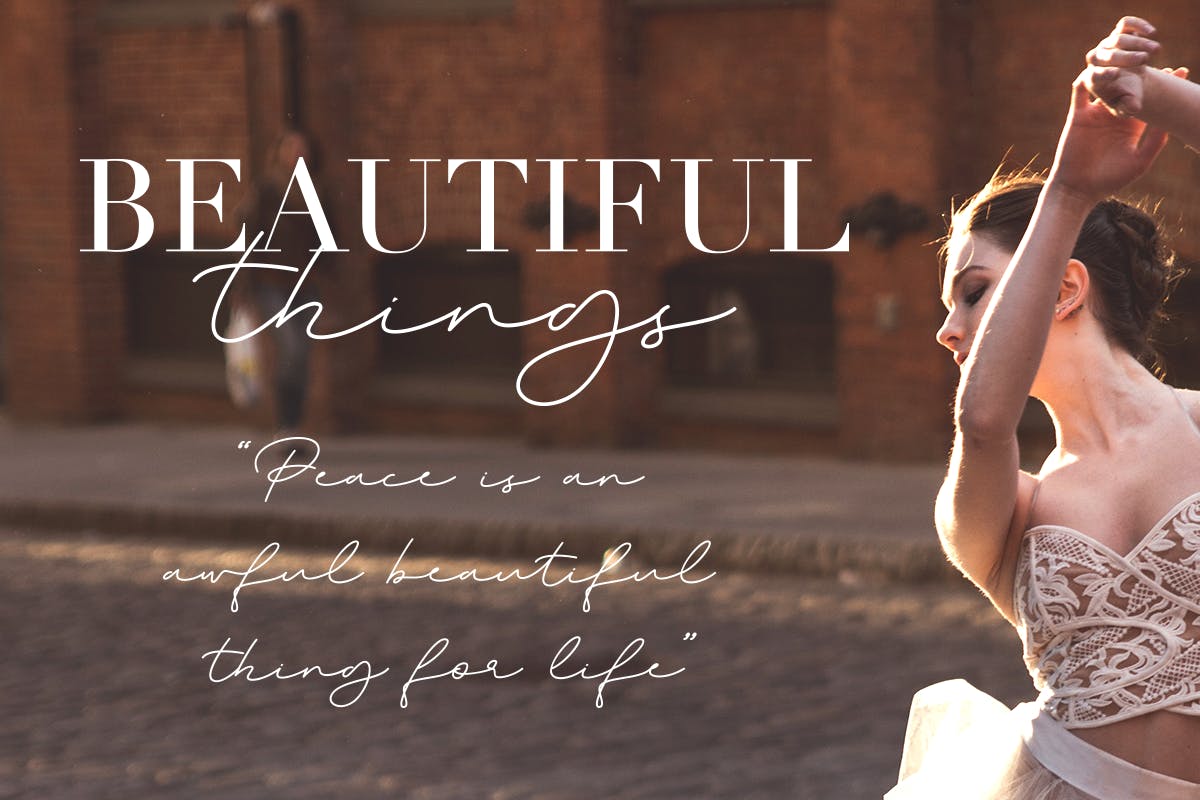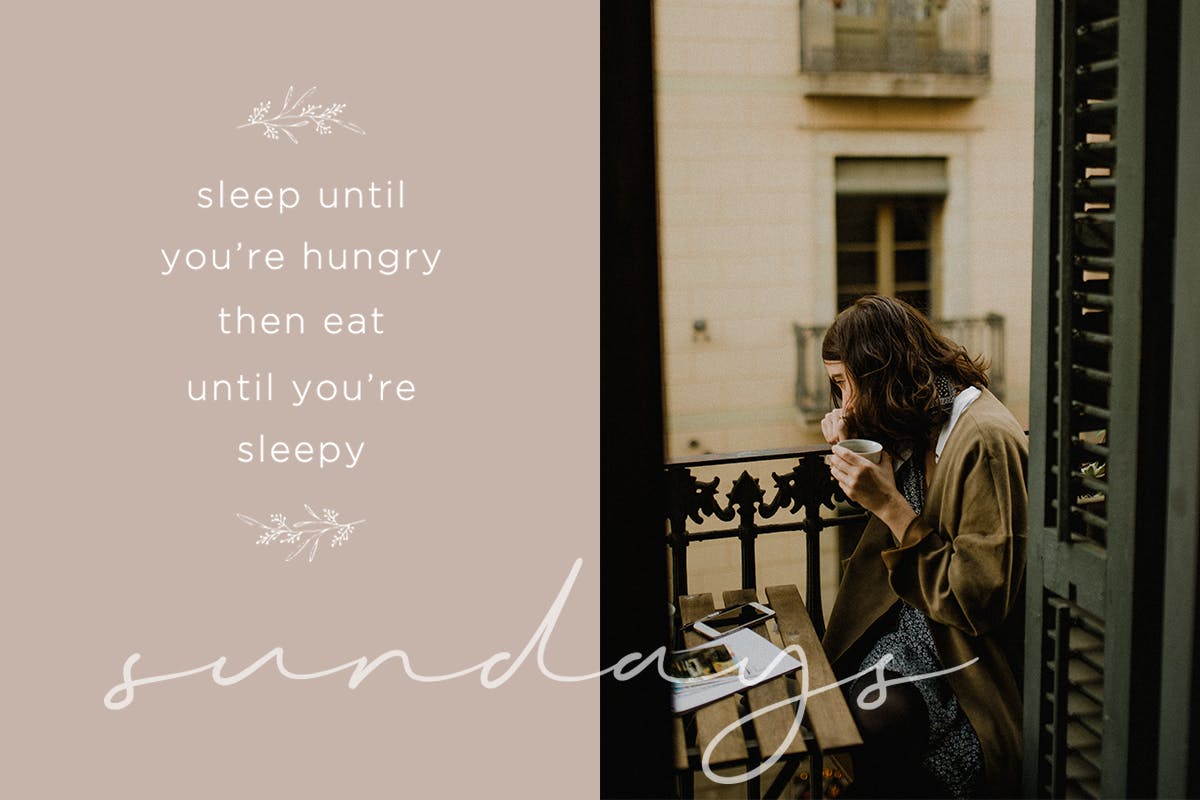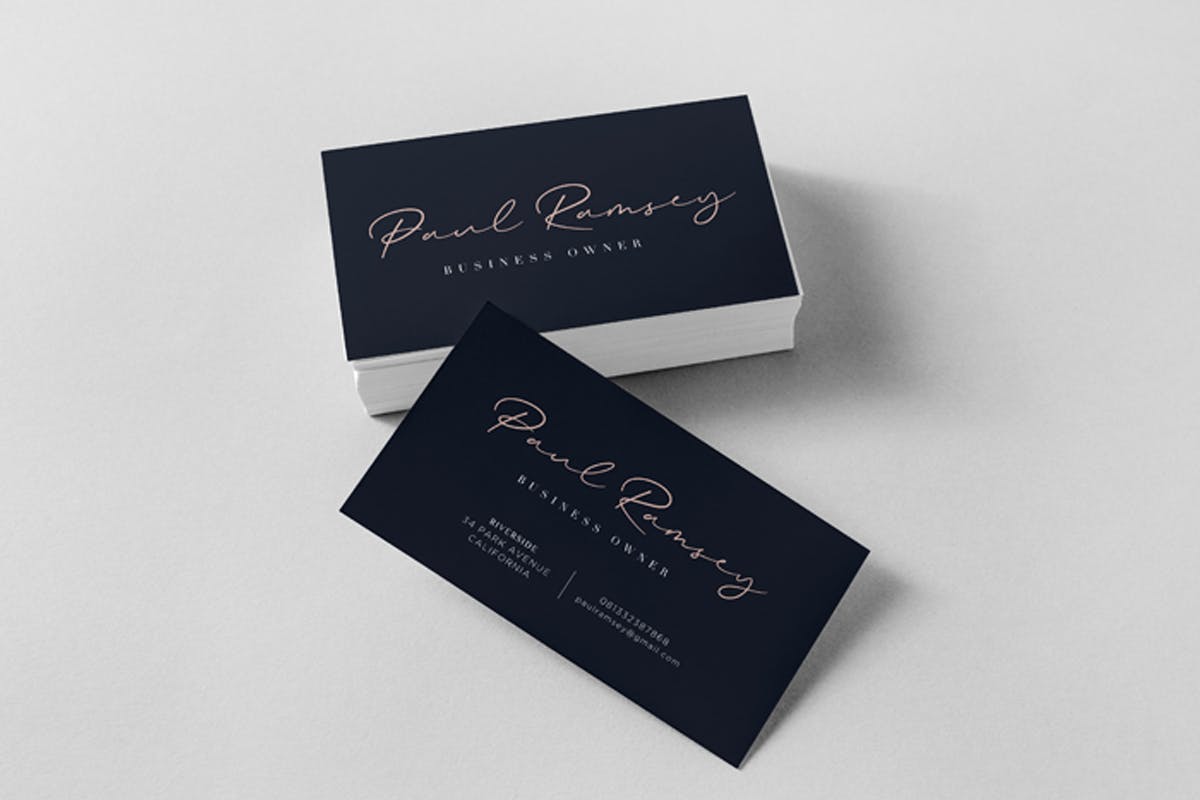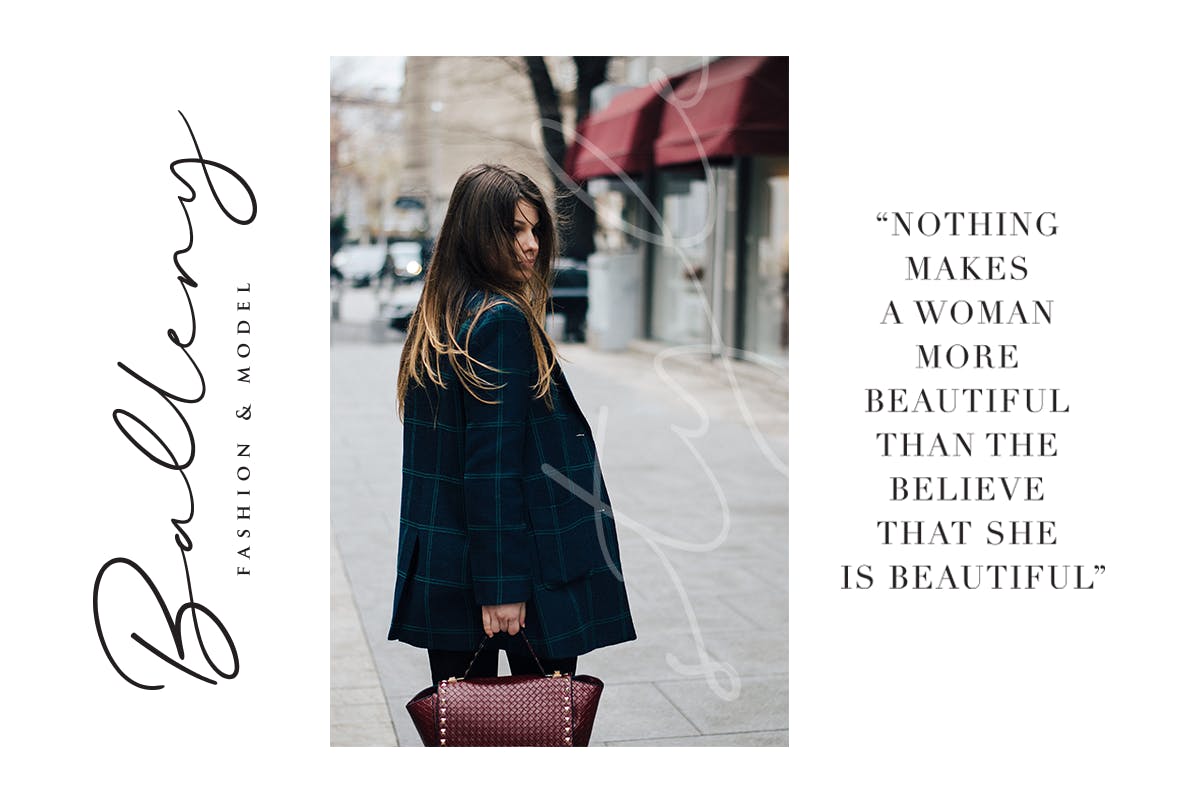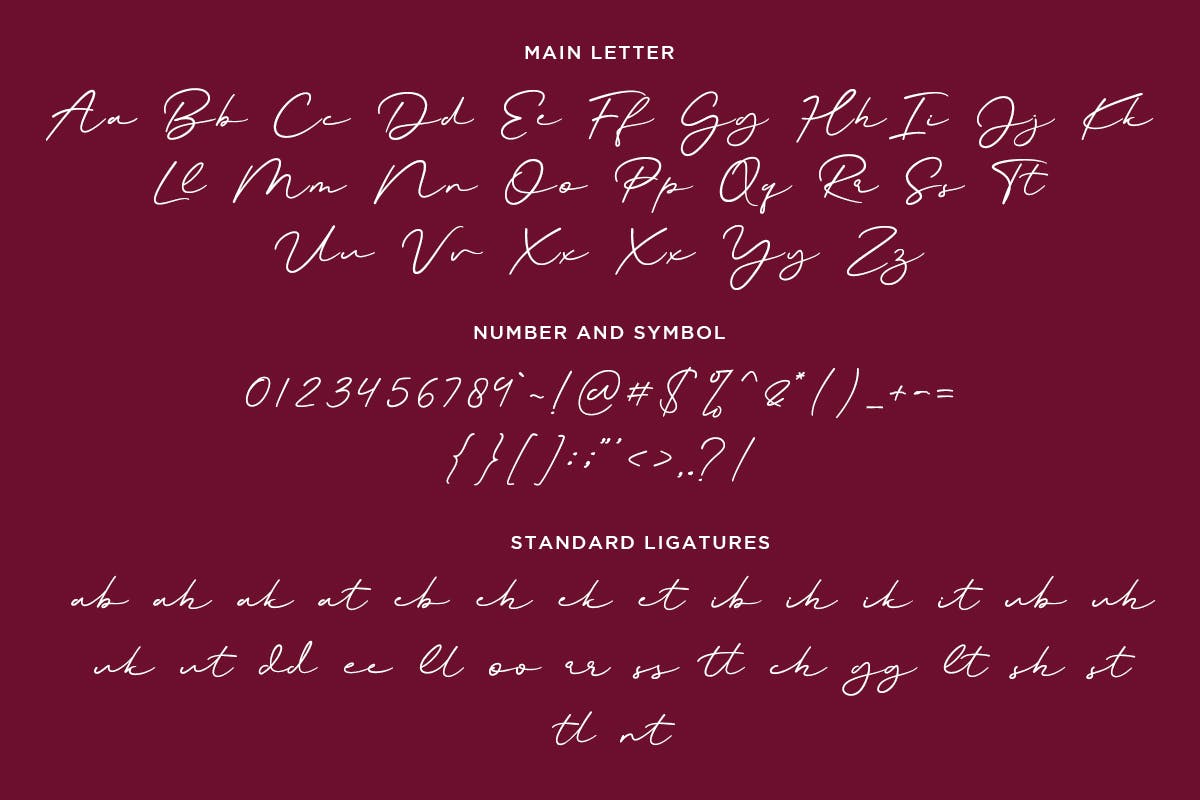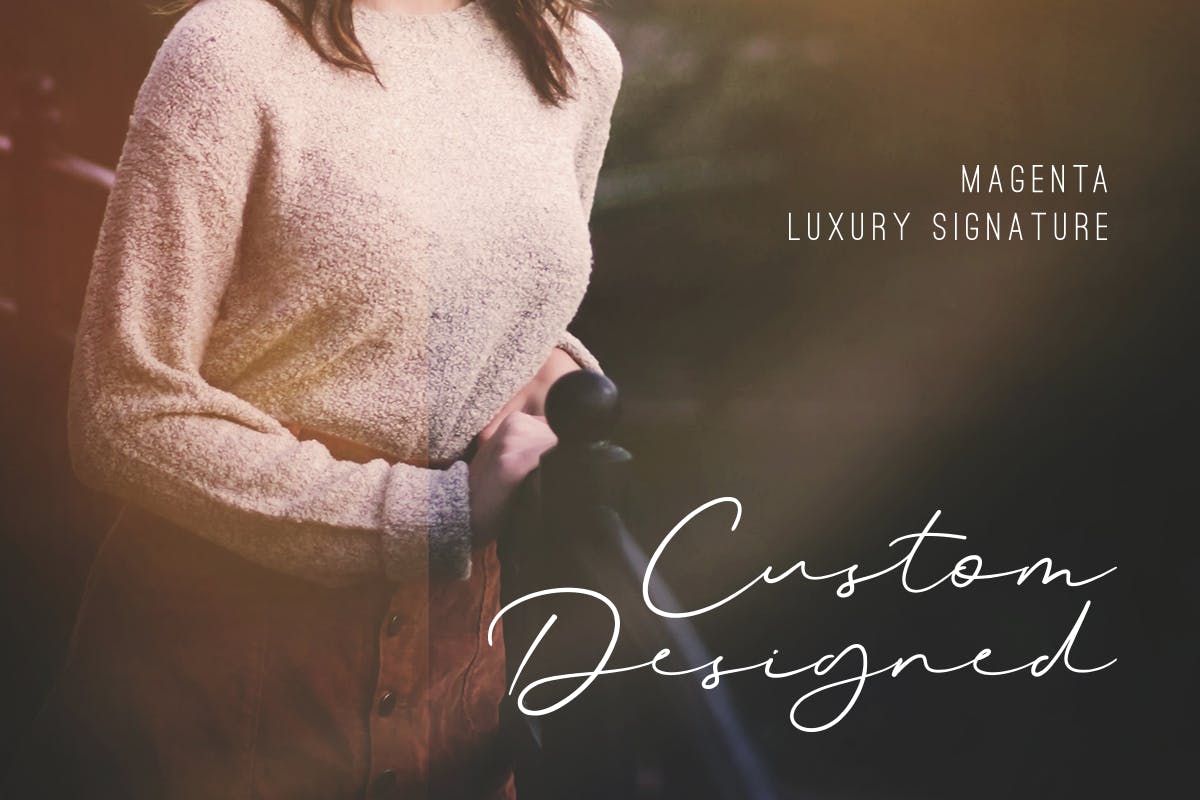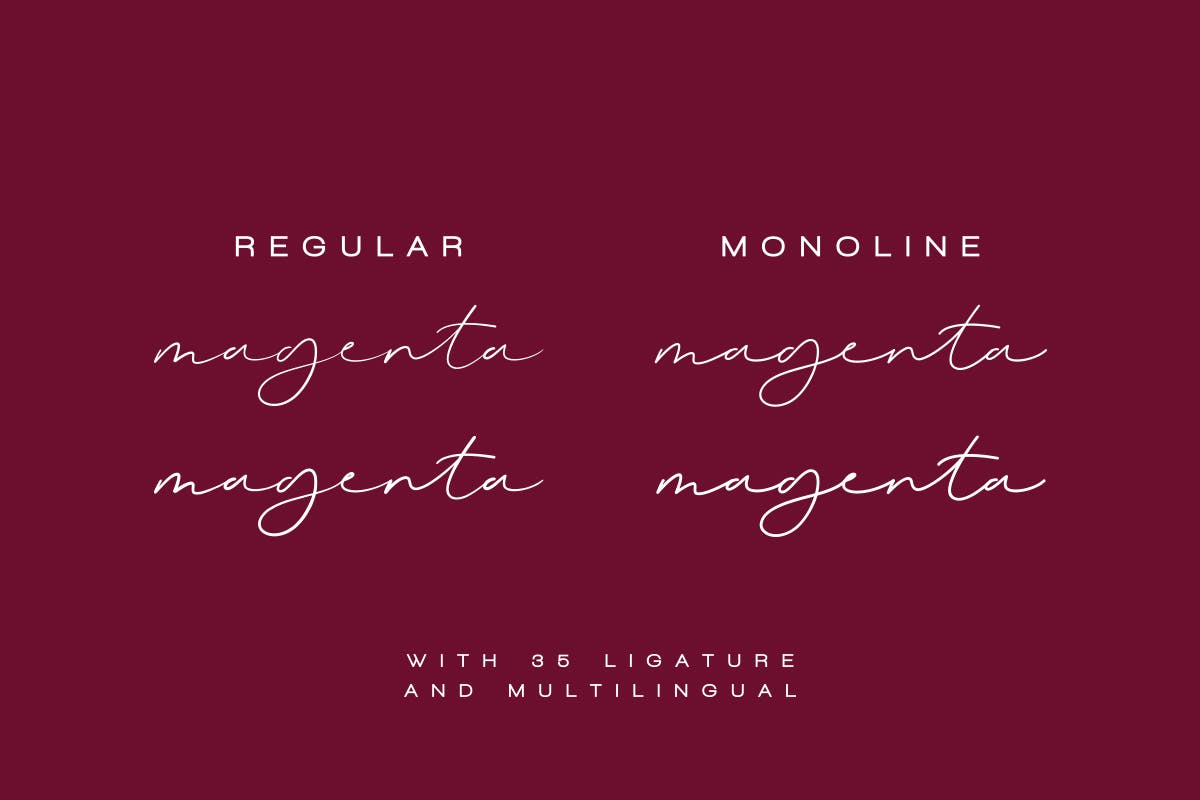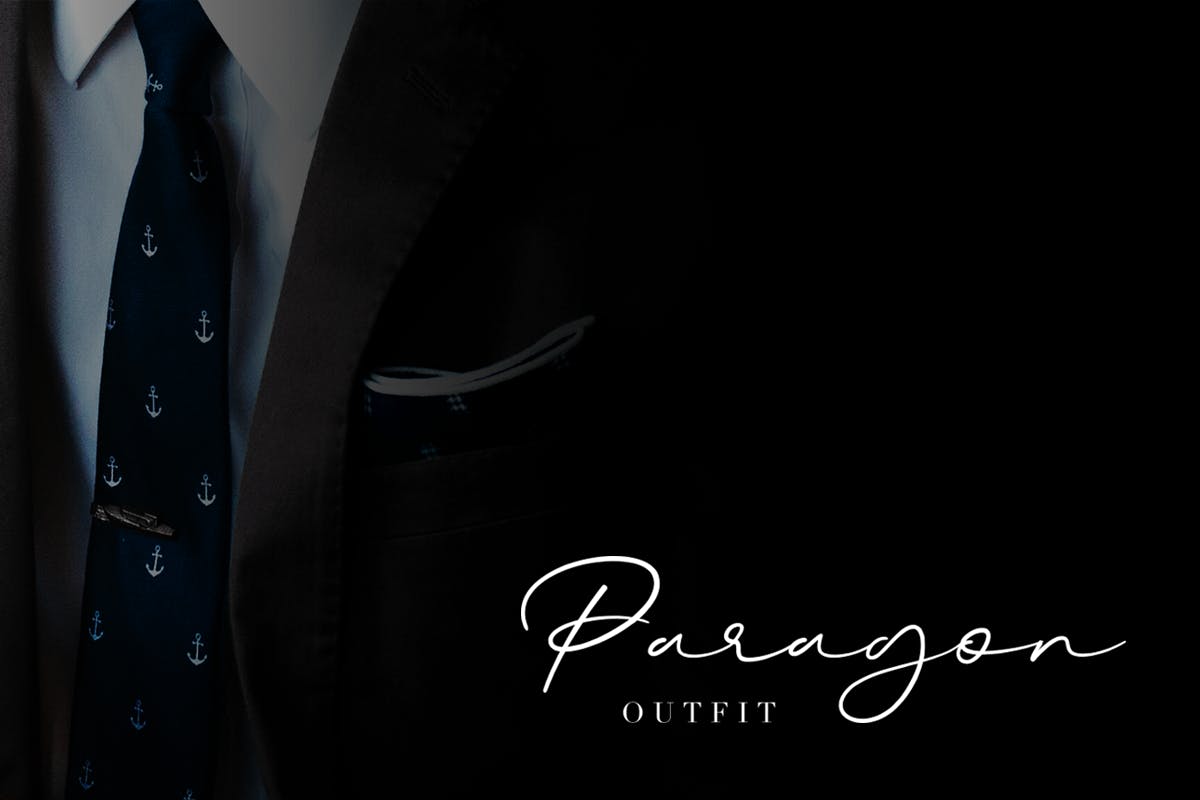
با Magenta آشنا شوید - فونت دست نویس لوکس و بدون دغدغه که با عشق و دقت طراحی شده است. این فونت گزینهای ایدهآل برای طراحان حرفهای به شمار میرود.
Magenta دارای ۲ نسخه است: نسخه امضا و نسخه مونولاین. این فونت برای لوگوهای امضا، نقل قولهای چاپی، وبلاگها، سرصفحههای شبکههای اجتماعی، بستهبندی محصولات و بسیاری دیگر از پروژهها مناسب است.